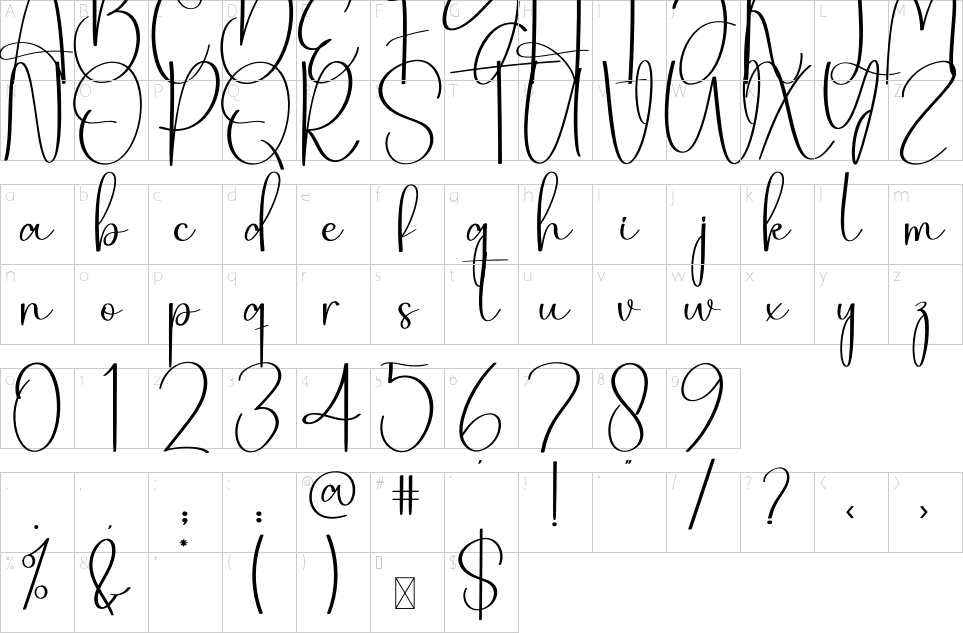
Aunty é uma fonte que traz consigo um toque divertido e acolhedor. Desenvolvida pelo designer scratchones, ela carrega consigo uma leveza e simplicidade que faz dela uma escolha perfeita para aqueles que desejam uma fonte elegante sem perder a sua personalidade. Com seu design criativo e sua versatilidade, Aunty é uma opção ótima para qualquer projeto que busca uma fonte agradável e versátil. Descarregada 513 vezes, ela tem demonstrado seu valor e popularidade entre os designers e criativos. Quem sabe você não pode ser o próximo a descobrir o brilho deste design único? Não perca tempo, instale Aunty e faça seu projeto brilhar!